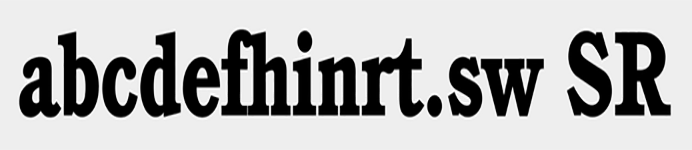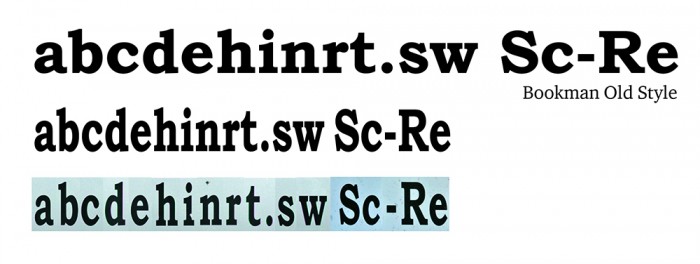
Schrift von LKW abfotografiert
Ein Schriftzug auf einem LKW gibt mir Rätsel auf. Kann mir jemand sagen, aus welcher Schriftart die Buchstaben entnommen sind. Eine Verzerrung kann einmal vom Abfotografieren kommen, wobei ich diese nach bestem Wissen korrigiert habe, aber auch schon in der Vorlage vorgelegen habe.
WhatTheFont sagt: Stymie Cond
Identifont sagt: Century Old Style
Beides haut nicht hin.
Eine gestauchte ITC Cushing Heavy?
Ich hab das auf 150 % gestreckt:
Ist sie nicht 100%ig …
Jaa, mit der Bookman Old Style komme ich hin, sofern ich sie um rund 35 % stauche.
Neulich war ich zugegen, als ein Werbetechniker ein Schild gestaltete. Er stauchte und schubste sich die Schriftzüge in Corel zurecht, dass es eine wahre Wonne war. Und das habe ich jetzt schon beim dritten Werbetechniker erlebt, mit dem ich häufiger zusammenarbeite.
Wird zeit, dass man in Fonts nicht nur das Einbetten, sondern viel wichtiger das nichtproportionale Stauchen sperren kann.